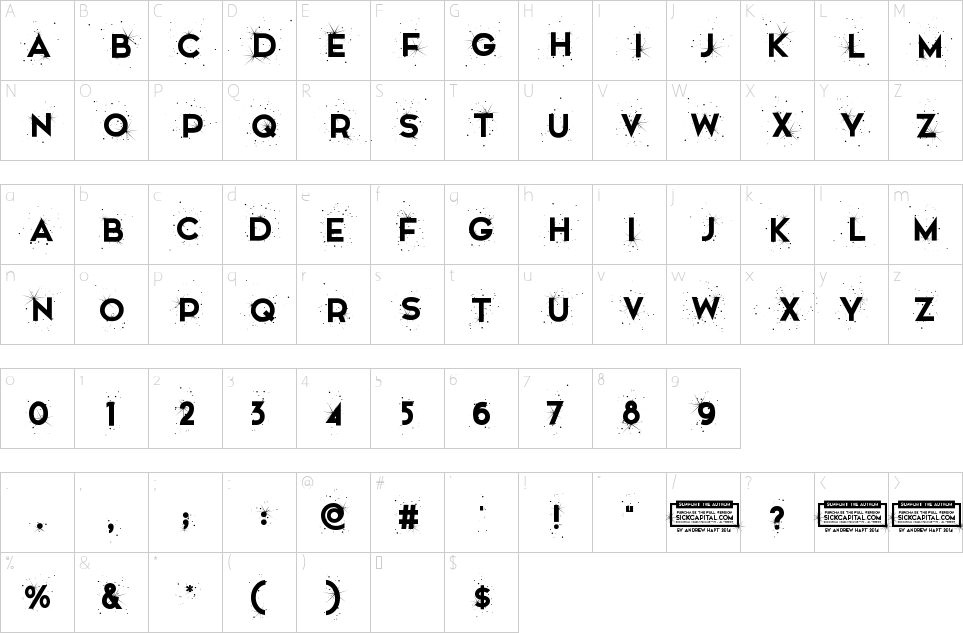
Snowinter Font – Download Grátis
A Snowinter é uma fonte de estilo neo-grotesca ideal para projetos digitais modernos. Desenvolvida por Dirt2, a fonte ganhou popularidade entre designers digitais e impressos. Com seu design elegante e versátil, a Snowinter torna-se uma opção preferencial para se destacar em design de interface de usuário, sites e redes sociais. Os usuários têm adorado seu equilíbrio entre leveza e robustez, o que torna-a uma escolha segura para designers iniciantes e profissionais. Atualmente, mais de 168.757 pessoas já baixaram a Snowinter font, o que demonstra sua grande aceitação entre o público. Se você está procurando por uma fonte com estilo único para enriquecer seus projetos digitais, a Snowinter é uma excelente opção.